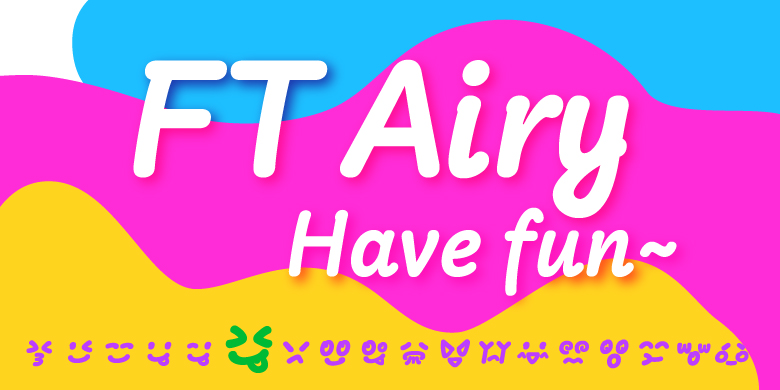
FT Airy
李雪婷
无衬线体
FT Airy,取意如空气般自在,核心表达自由、松弛感与趣味变化。灵感源于年轻人对自由、挑战和未知的追求。字形倾斜灵动,笔画圆润流畅,成句具韵律美;笔画简洁有力,造型活泼俏皮,松弛感十足。圆润俏皮的字形契合儿童审美,清晰易读的设计更适合儿童绘本场景,能让孩子直观感受文字的趣味。字库全面覆盖拉丁扩展、希腊、西里尔字符集,同时支持保加利亚语等多语种排版需求。创新融入表情符号Emoji与生肖字母设计,前者丰富应用趣味,后者赋予字库中国传统文化底蕴。适用于户外标语、综艺包装、儿童绘本及各类年轻品牌宣传物料。